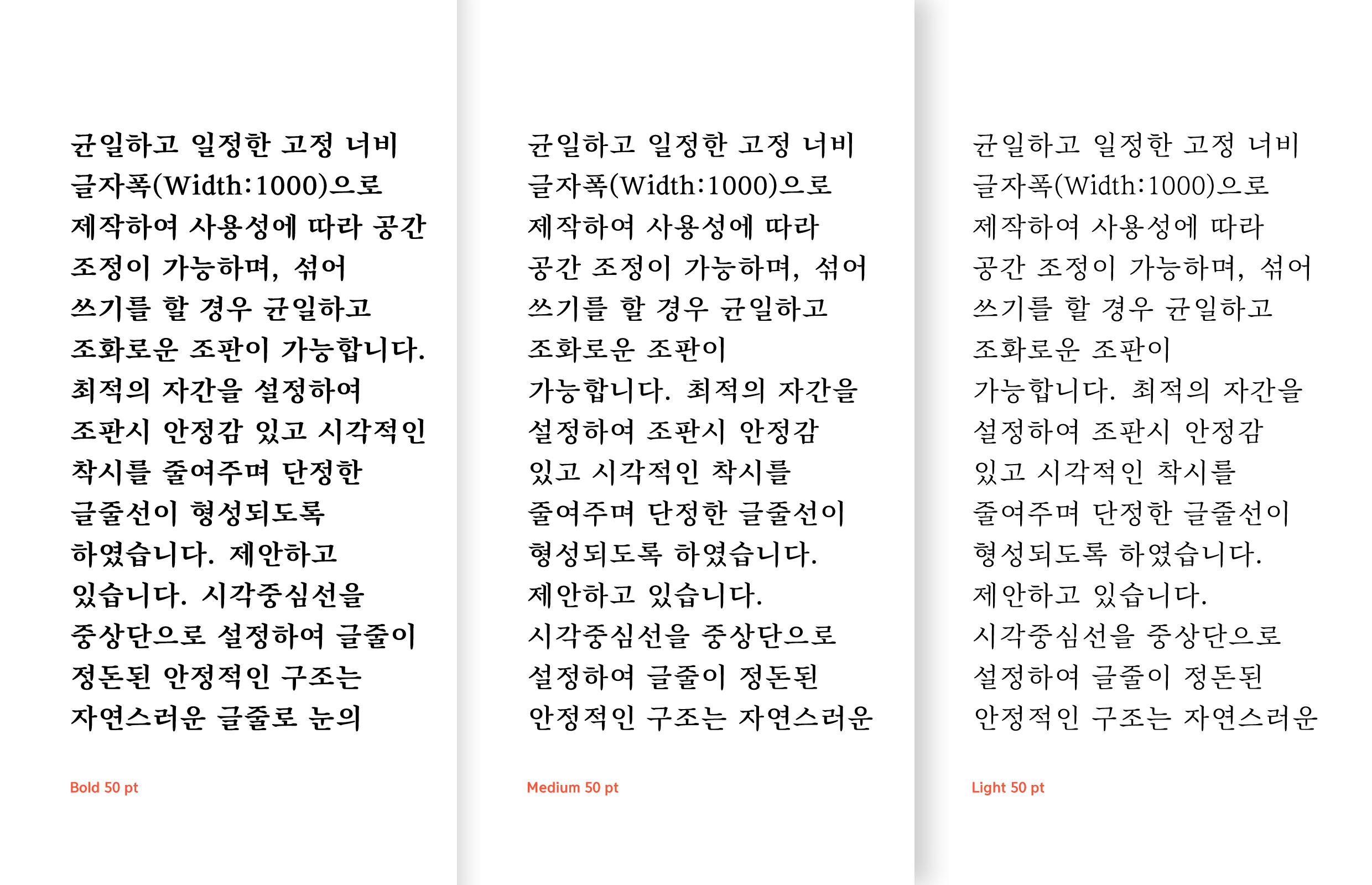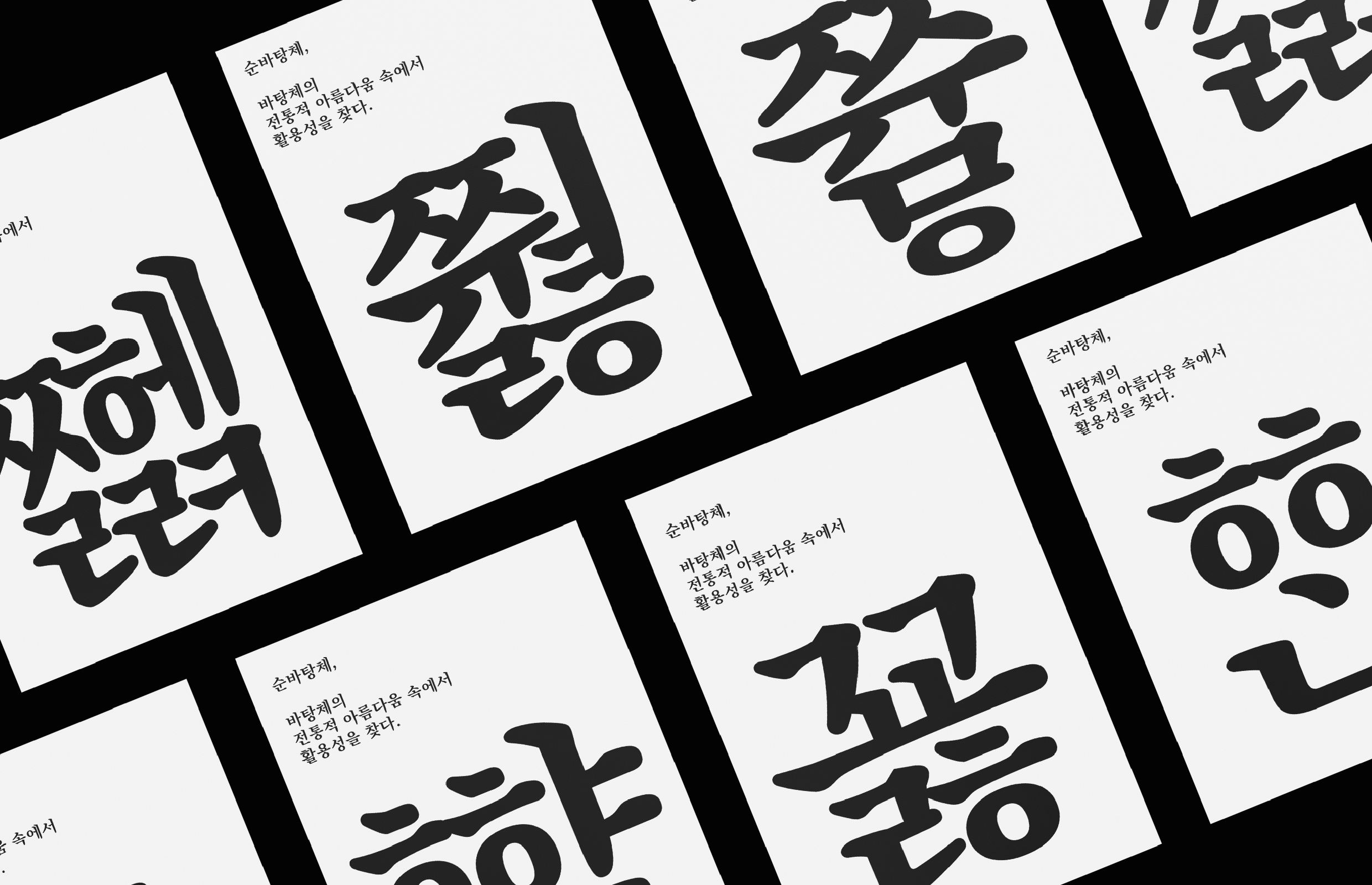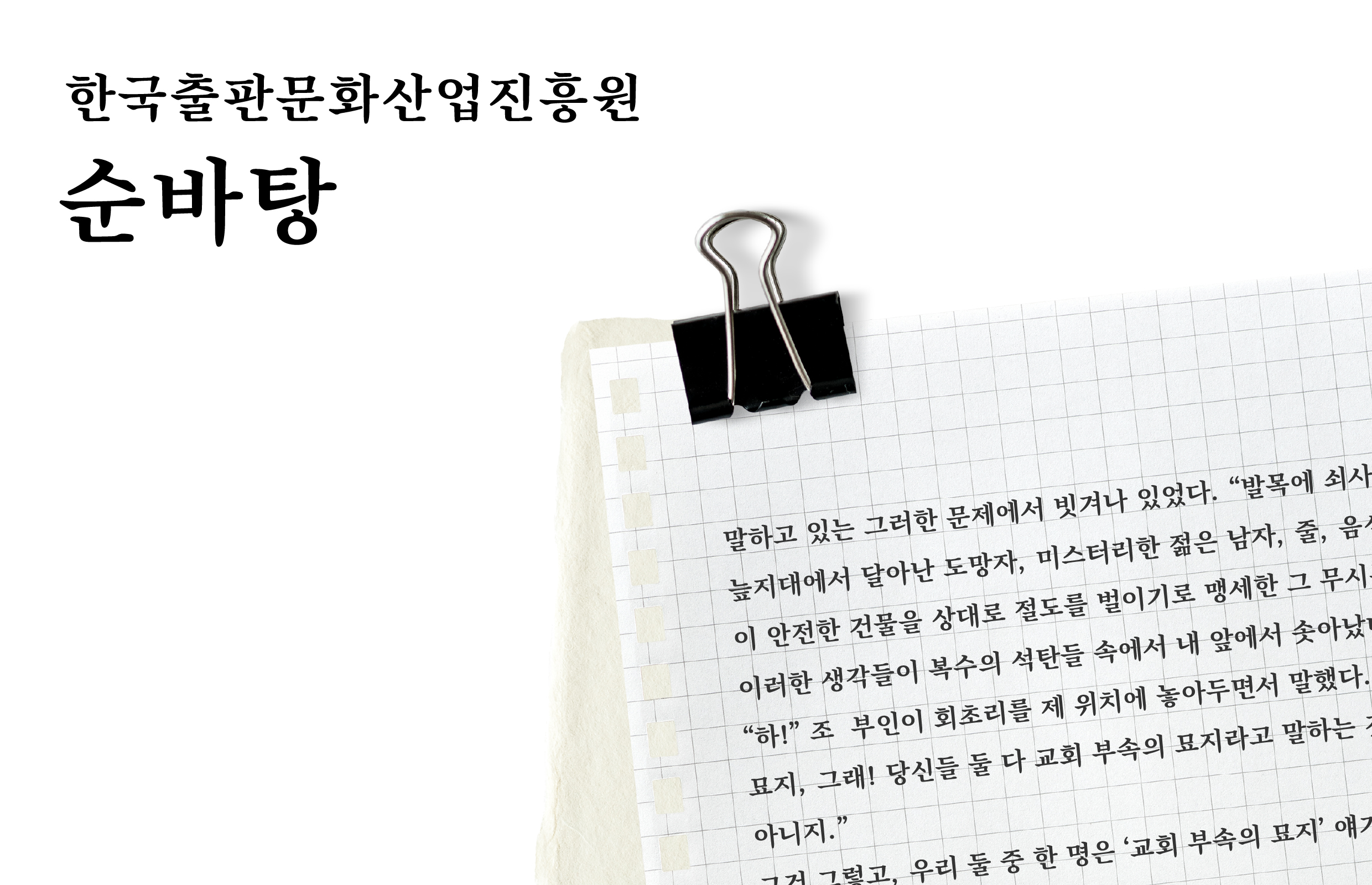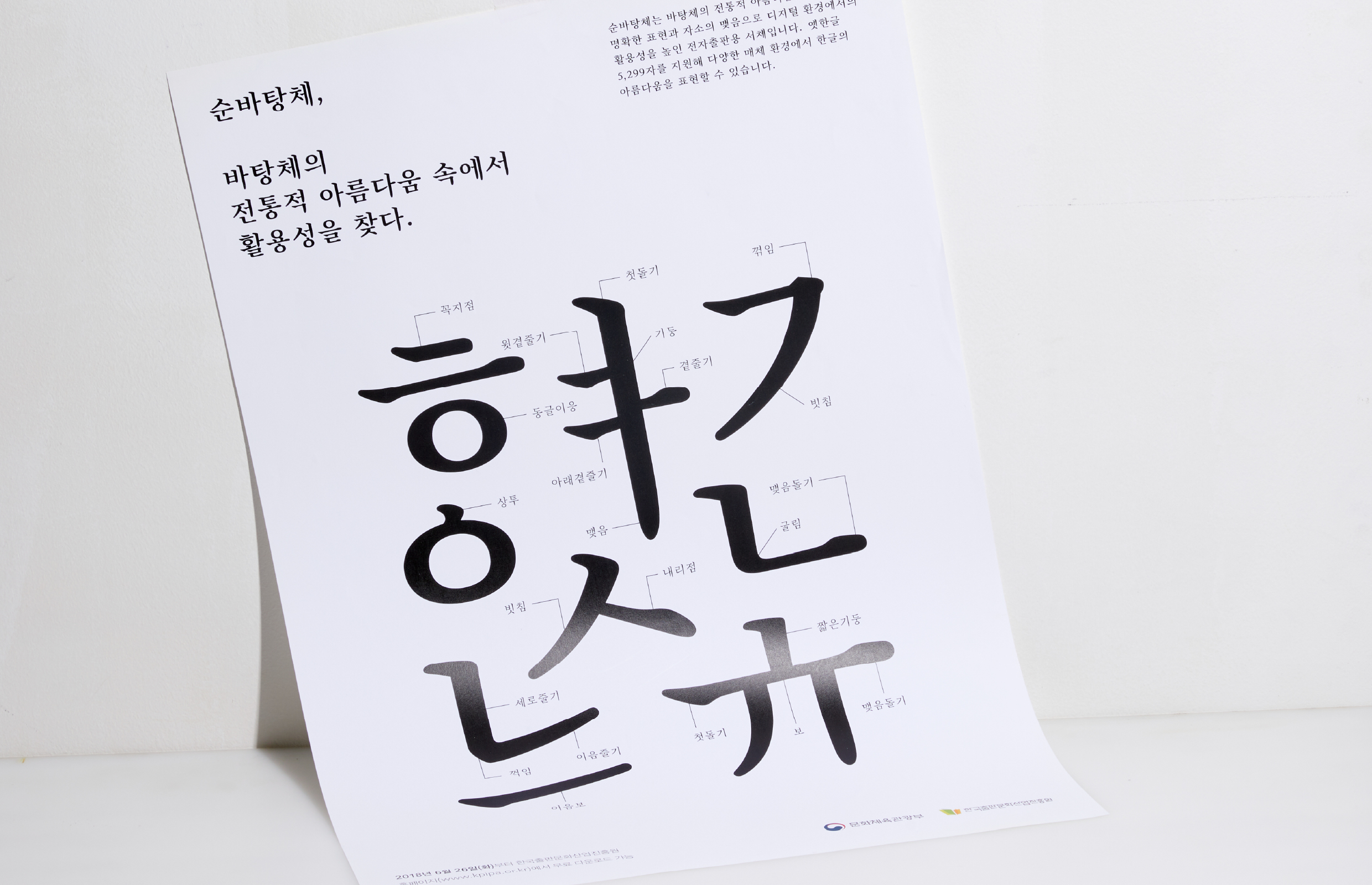
한국출판문화산업진흥원 [순바탕]
R순바탕은 오픈소스형 디지털 서체로, 상업용 서체 사용에 따른 비용 부담 및 지적 재산권 분쟁 방지를 목적으로 개발되었다. 바탕체의 전통적인 요소들은 유지하되, 정확한 표현과 맺음으로 전통적인 아름다움을 살리고 현대화함으로써 디지털 환경에서 활용성을 높였다.